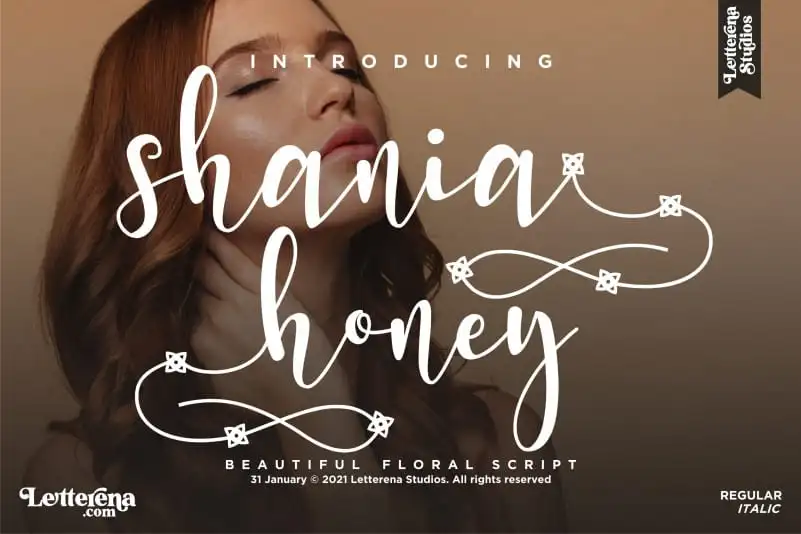
A Shania Honey Calligraphy Font, criada pela Letterenastudios, é uma opção perfeita para qualquer projeto que busque agregar sofistica e romantismo à sua tipografia. Esta fonte romântica de caligrafia se destaca por seu ar elegante e encantador, tornando-a perfeitamente adaptável a uma vasta gama de ideias de projeto. A Shania Honey Calligraphy Font é indicada para qualquer aplicação que exige um toque delicado e artesanal, desde as logomarcas e projetos de marca até os produtos de embalagem, as t-shirts personalizadas ou até mesmo o design dos envelopes de presente. Seja você criando uma identidade visual única, decoração de casa, artesanato em homenagem à moda ou até mesmo um projeto para celebrar algum evento especial, a Shania Honey Calligraphy Font oferece a elegância que seu trabalho precisa. Suas linhas delicadas e traços suaves fazem deste um recurso indispensável para designers buscando uma fonte de caligrafia script única e sofisticada.